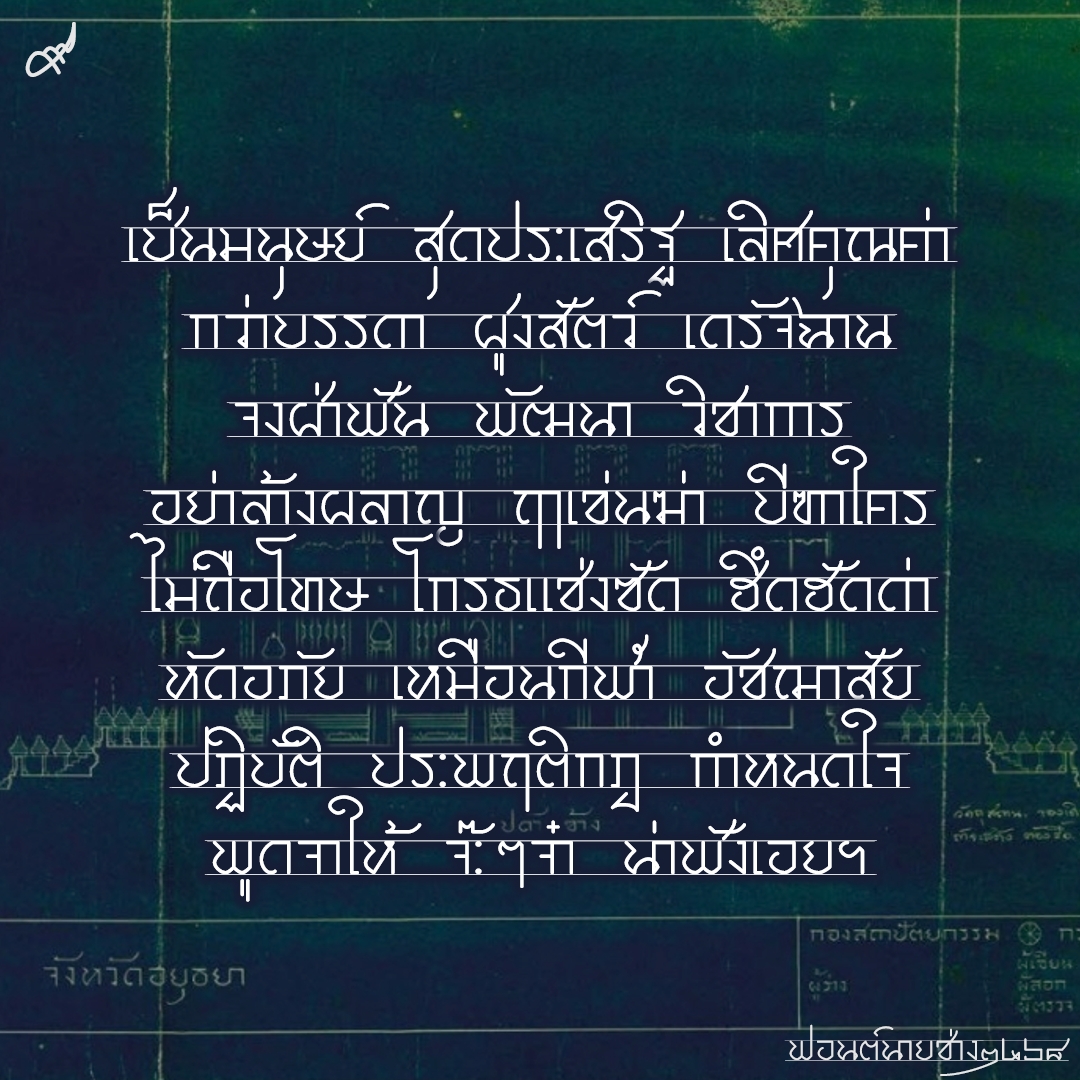
ฟอนต์ นายช่าง2468
ฟอนต์นายช่าง2468 ต้นทางจากอักษรของสมเด็จครูที่พบในพิมพ์เขียวงานสถาปัตย์ เมื่อประมาณร้อยปีที่แล้ว ร่างเส้นขึ้นมาใหม่ ชอบความมีเส้นบรรทัดเลยเติมเข้าไปด้วย ใช้เป็นข้อความ หากอยากได้พาดหัวให้กด bold
ชื่อฟอนต์ : นายช่าง2468
ฟอนต์นายช่าง2468 ต้นทางจากอักษรของสมเด็จครูที่พบในพิมพ์เขียวงานสถาปัตย์ เมื่อประมาณร้อยปีที่แล้ว ร่างเส้นขึ้นมาใหม่ ชอบความมีเส้นบรรทัดเลยเติมเข้าไปด้วย ใช้เป็นข้อความ หากอยากได้พาดหัวให้กด bold
:18: ตัวนี้ทรงคุณค่ามากครับ
เพิ่งค้นพบเล่มนี้ มีหัวข้อแบบอักษรโดยเฉพาะด้วย
จากเล่มของ อ.ประเวศ สุดยอดมากๆ เลยครับ :25: